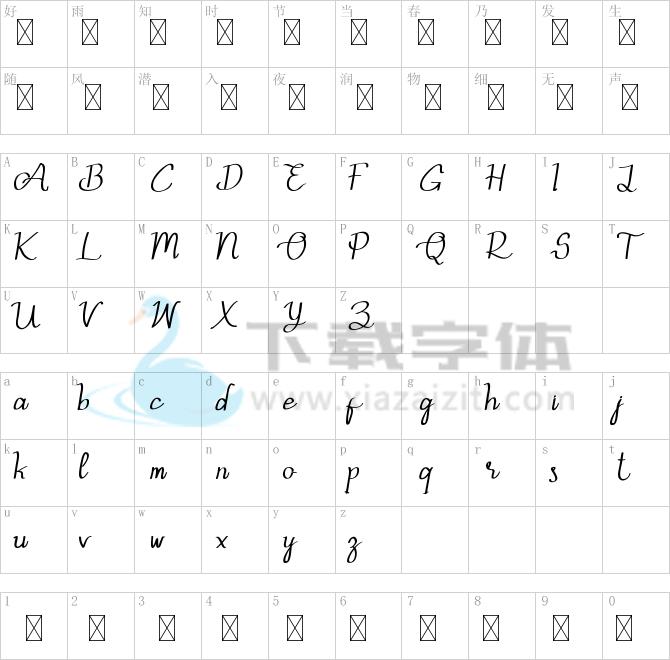
Aslina Ohio Demo.ttf字体下载,这款字体结构工整、笔画清晰,兼顾美观与易读性,适用于标题、正文、海报、包装、LOGO 等多种场景。字形优雅稳定,风格百搭耐看,适配日常排版与创意设计,让文字呈现更舒适、更具质感。Aslina Ohio Demo.ttf字体下载一笔一画,皆是细节,以均衡的比例、流畅的线条打造舒适视觉体验,字形端正大气,风格简约现代。无论是商业设计、品牌宣传还是日常排版,都能轻松驾驭,让文字更有格调与力量。Aslina Ohio Demo.ttf字体下载字体下载。